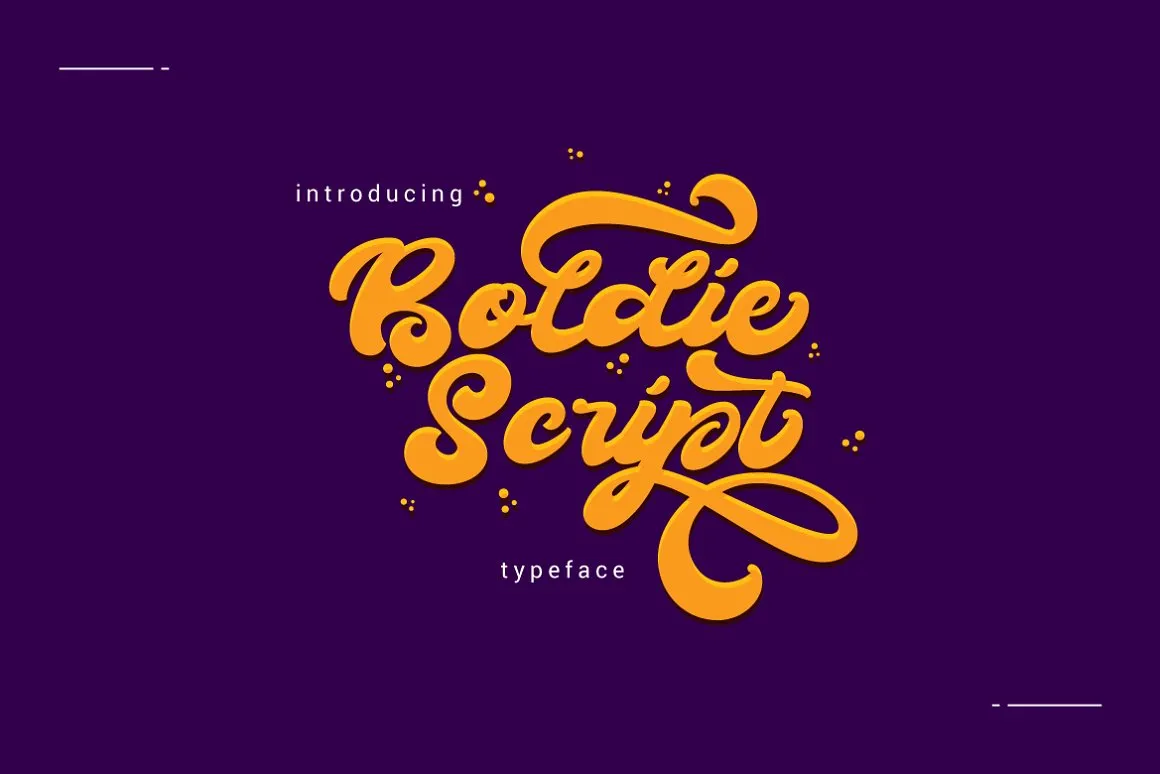
Esse novo Boldie Script Font é uma adição fascinante ao universo das fuentes script! Desenvolvida pelo talentoso Designer Hamilton, esta opção vem trazer simplicidade e facilidade para criar letravers criativos. Ideal para quem busca uma fonte que facilite o trabalho em criações de letra personalizadas ou design gráfico. Basta digitar suas palavras e você verá imediatamente os resultados incríveis gerados por Boldie, sem precisar de muito ajuste. Afinal, a simplicidade é essencial para quem quer focar nas criativas ideias que o seu projeto pode conter. Não perca esta oportunidade de tornar ainda mais especial o design de seus projetos com Boldie Script Font.